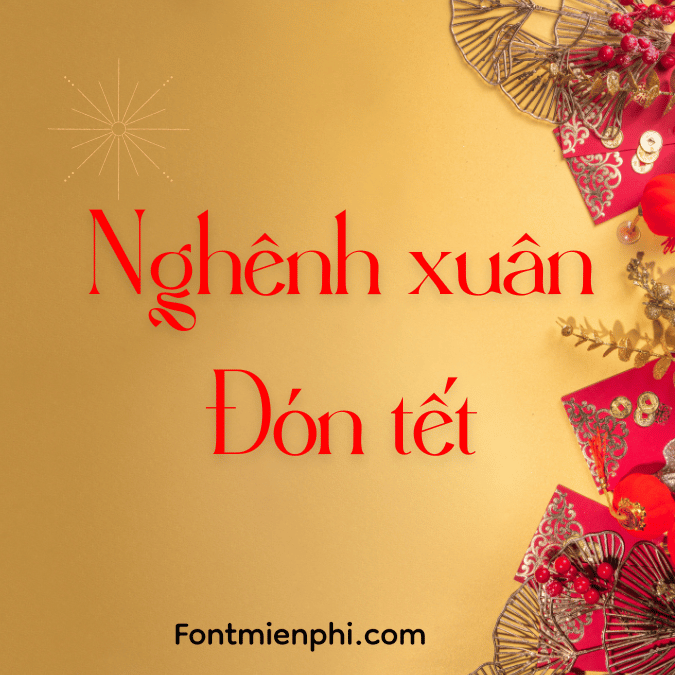
FONT VIỆT HÓA 1FTV VIP ANGRELA DISPLAY
“Tinh hoa typography phong cách Châu Âu đích thực”
ĐẶC ĐIỂM NỔI BẬT
✨ Kiểu chữ Display sang trọng: Lấy cảm hứng từ các bảng hiệu cao cấp tại Paris và Milan, với nét chữ thanh lịch, độ tương phản hoàn hảo
Hiệu ứng gradient tự nhiên: Được tối ưu để tạo hiệu ứng chuyển màu mượt mà ngay trong file font
Tối ưu đa ngôn ngữ: Hỗ trợ hoàn hảo tiếng Việt + bộ ký tự Latinh mở rộng
ỨNG DỤNG CAO CẤP
• Thiết kế logo thời trang xa xỉ
• Bộ nhận diện nhà hàng, khách sạn 5*
• Bao bì mỹ phẩm và nước hoa cao cấp
• Tạp chí thời trang và thiết kế nội thất
BỘ VIP ĐẶC BIỆT
5 phiên bản độc quyền:
- Regular (nét chuẩn)
- Gradient (chuyển sắc tự động)
- Outline (viền tinh tế)
- Serif (biến thể có chân)
- Extended (nét rộng sang trọng)
“Angrela Display – Đẳng cấp được khẳng định từng con chữ!”
GỢI Ý THIẾT KẾ
• Màu sắc: Vàng kim #D4AF37 + Đen #000000
• Phối cảnh: Hiệu ứng đổ bóng đa tầng
• Texture: Giấy bồi sang trọng, vân gỗ cao cấp